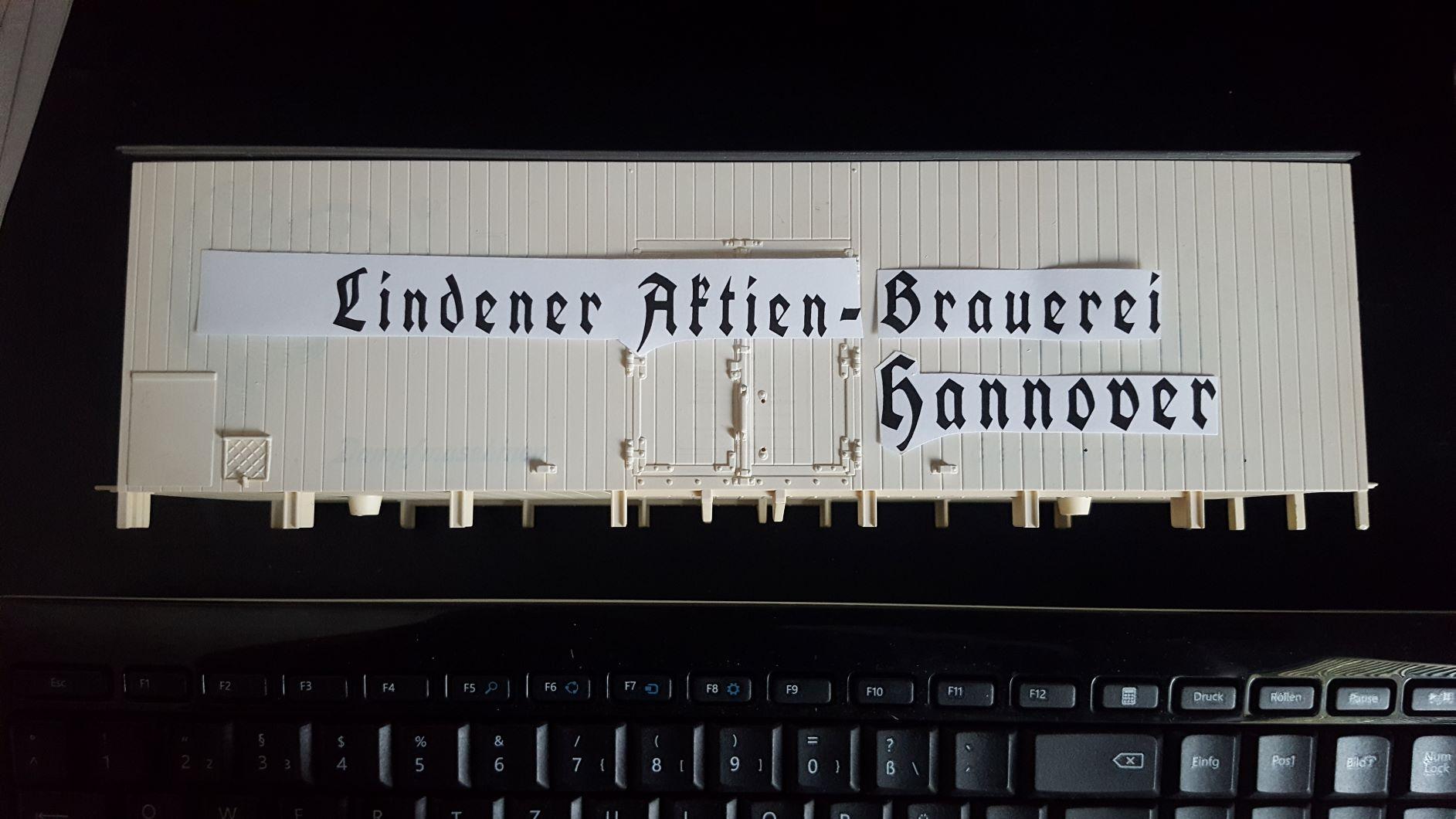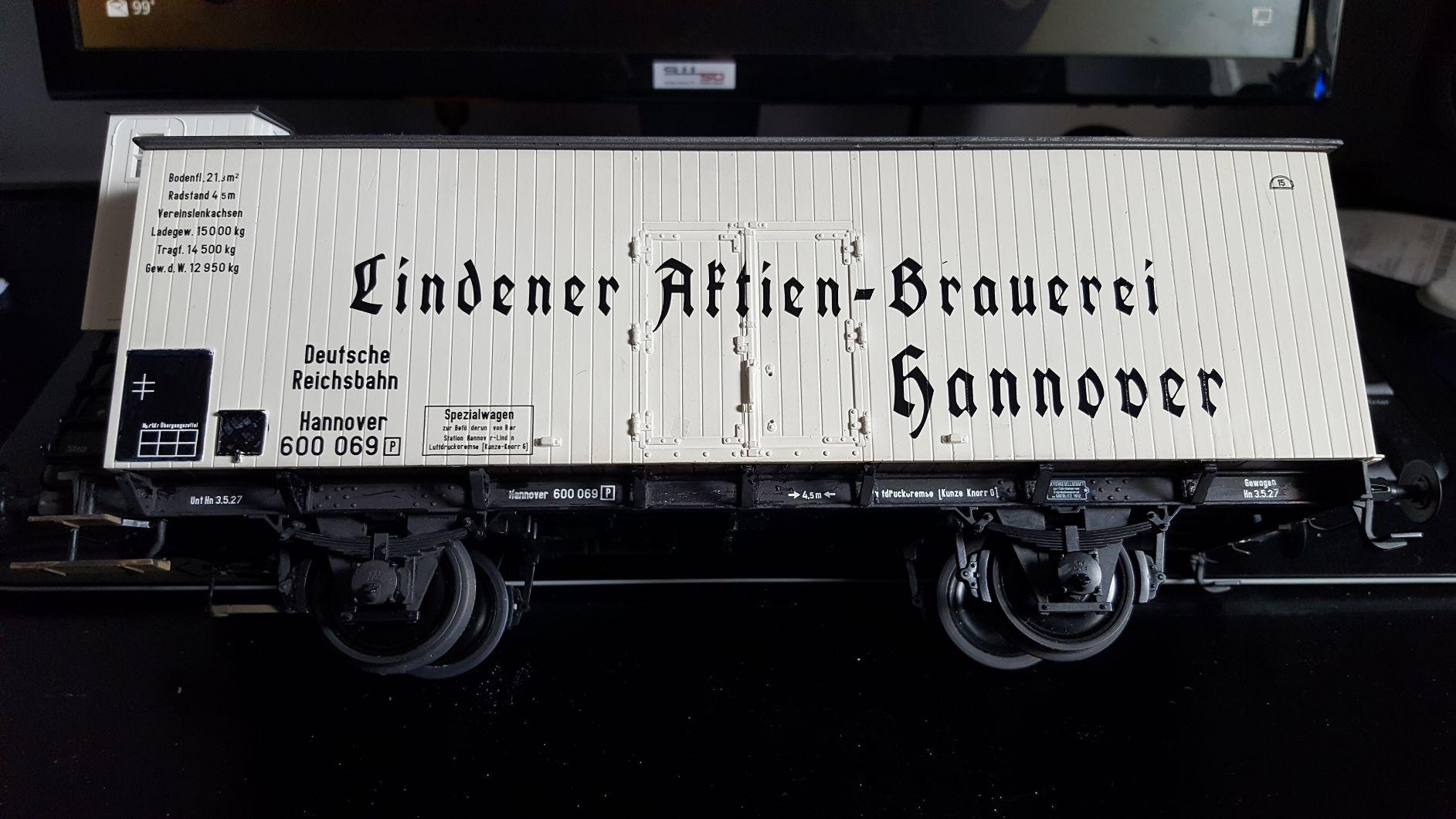
Ich suche den Namen und mögliche Quellen, der auf dem Eisenbahnwagen gezeigten Schriftart
Zwecks Nachbau dieses Kühlwagens der Lindener Brauerei Hannover aus den vermtl. 20er Jahren suche ich diese Schrifttype möglichst exakt.
Es handelt sich bei dem Bild um ein Werksfoto der hannoverschen Waggonbau aus dieser Zeit, andere Quellen in besserer Auflösung sind mir leider nicht bekannt.
Hier ist noch ein bissl größeres Bild:
Tja, da muss ich dich wohl oder übel auf den Boden der Tatsachen herunterholen. Bis sogar noch in die 1970er Jahre gehörte es zur Ausbilduns aller Berufe, die größere Beschriftungen außerhalb von auf  bedrucktem Papier herstellten, zu lernen, wie man die grundsätzlichen Schriftstile entwirft und konstruiert. Einen Zugang zu benannten Druckschriften hatten diese Berufe in der Regel nicht, da sie in der Regel auch gar nicht in eine Setzerei hineingelassen wurden, um sich da durch die vorhandenen Setkästen wühlen zu dürfen, um da ein  paar Worte als Vorlage setzen zu lassen, welche die dann auch noch auf die benötigte Größe auf schweineteurem Fotopapier beim Repro-Fotografebn dann hochzu skalieren. Auch waren Satzschriften auch gar nicht dafür gedacht, Beschriftungen in dieser Größe anzufertigen.
Solche Arbeiten war also die Aufgabe von Schilder- und Reklamemalern, aber auch Lackierern, oder auch Steinmetzen.
Zudem ist deine Vorlage so klein, dass man hinter den Pixeln kaum die Schrift, sollte sie vielleicht doch schon digitalisiert worden sein, auch sicher zu erkennen. Was man in Filmen immer wieder sieht, dass da ein verpixeltes Überwachungskamera-Bild gezeigt wird, das der Komputer-Spezialist ruck zuck zu einem scharfen Fahndungsfoto vergrößert, ist leider ein Film-Märchen. Aus einer Zeichenhöhe von gerade einmal 10 Pixeln bei den Kleinbuchstaben lässt sich mit besten Willen kein Buchstabe erkennen.
Das einzige, was ich dir empfehlen könnte, währe mal beim Kollegen Helzel vorbei zu schauenm, immerhin hat der mittlereiile 450 Frakturschriften digitalisiert.
die Schrift hat eine starke Ähnlichkeit mit der Koch-Schrift auf Reichsbahnschwabacher genannt. Ist aber trotzdem keine Schwabacher sondern eine Fraktur. Ein anderer Name lautet Fette Deutsche Schrift. Die Schrift auf dem Bild erscheint aber etwas leichter.
Typeface:	Koch Schrift
Desigener:	Rudolf Koch
Year:		1909
Kräftige Schwabacher;
gute Alternative zur „AltenSchwabacher“;
nach einem Druckmuster ca.1930;
Rudolf Kochs erste Druckschrift von 1909
Auf einem alten Schriftmusterblatt aus den 30er Jahren wird
diese Schrift als „Schwabacher (bei der Deutschen Reichsbahn
verwendet)“ bezeichnet.
In Wahrheit handelt es sich um die berühmte erste Schrift des
Schreibmeisters Rudolf Koch, die dieser im Jahre 1909 für die
spätere Schriftgiesserei Gebr. Klingspor schuf. Damals erhielt
sie den Namen „Neudeutsch“. Später erlangte sie als Koch-
Schrift Berühmtheit. Sie wurde in den 30er Jahren tatsächlich
die Hausschrift der Deutschen Reichsbahn.
Es gibt  auch eine freie Digitalisierung.
Vielleicht reicht das ja schon aus?
Wow, schon mal vielen Dank für die Hinweise..."fette Deutsche Schrift" kommt dem Bild am nächsten, allerdings tatsächlich zu "fett".
Koch-Fraktur normal  passt auch, leider nicht beim "A" und "H"...,
Klar das der Wagen nicht bedruckt, sondern wohl mit Schablone "beschrieben" wurde, allerdings sind die Anschriften an Eisenbahnfahrzeugen, zumindest für die Revisionsdaten und Eigentumsbeschriftungen genormt gewesen...
Evtl. lässt sich etwas passendes "zusammenstückeln"
Die Richtung passt....😎
, sondern wohl mit Schablone "beschrieben" wurde,
Üblicherweise hatten die Schildermaler für so große Beschriftungen keine Schablonen, sondern haben das von Hand gemacht.
Nach einigem Probieren konnte ich aus der "fetten Deutschen Schrift" durch Skalieren und weiß konturieren ein für mich akzeptables Schriftbild am PC mittels Standart-Software erzeugen. Immer wieder beachtlich, was moderne Digitaltechnik, zu leisten vermag.
Anbei die erste Umsetzung am Modellfahrzeug im Maßstab 1:32... später auf Anreibefolie gedruckt, wird es ein sauberes Ergebnis geben...
Wenn man jetzt noch bedenkt, dass sich die Lindener Actien-Brauerei damals mit c statt k geschrieben hat …
Das hat aber wohl der Reclamemaler wohl übersehen, und den Wagon mit k beschriftet.
Das Wort Aktie entstand wohl ab 1472 in Bremen aus dem mittelniederdeutschen Wort „axie“ für „Anspruch“ oder „Anrecht“, das sich aus dem Begriff für den „Klageanspruch“ (lateinisch actio) ableitete. Zitiert wird die Aktie in Bremen wie folgt: „van Antworpe in der zone nicht mede wesen unde up erer axien stande bliven wolden“. Im Jahre 1598 wird aus Wijk bij Duurstede zitiert: „So wie eine Anleihe, Obligation oder Aktie von jemand kauft…“ (niederländisch soo wie een rentebrieff, obligatie ofte actie van ymant coopt) Die holländische Niederländische Ostindien-Kompanie gab im März 1603 erstmals Aktien (niederländisch actien in de compagnie) aus, wobei das niederländische Wort als Vorbild für die deutsche Sprache gedient hat. Im deutschsprachigen Raum lässt sich die Bezeichnung Aktie  (Actie) im heutigen Sinne erstmals 1647 in der Wendung „…dieſer brandenburgiſcher compagnien actien…“ nachweisen, 1651 sprach der Autor von der „Verkaufung der Actionen“. Aus dem Lateinischen leiten heute viele Sprachen ihren Aktienbegriff ab (italienisch azione, französisch action, spanisch acción).
wollte nur mal kurz das nahezu fertige Ergebnis der "Schrifttyp-Recherche"  einstellen....
Es hat sich alles gut gefügt...
Passt doch ganz gut …
Für mein Gefühl allerdings zu sehr gesperrt (zu viel Abstand zwischen den Buchstaben) 🤔
»Anyone who would letterspace blackletter would steal(?) sheep«